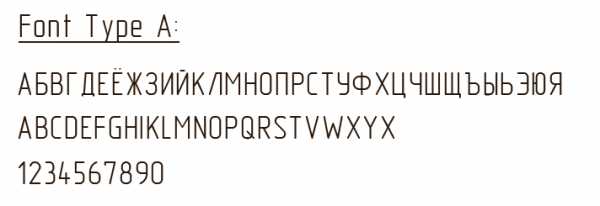
Размер шрифта h — высота прописных (заглавных) букв и цифр измеряемая в миллиметрах. Стандарт устанавливает следующие размеры шрифта: 1,8; 2,5; 3,5; 5; 7; 10; 14; 20; 28; 40. Высота строчных букв определяется по соотношению c = (7/10)h или если шрифт дан An то его высота строчных букв может быть взята по размеру шрифта An-1. Например размер шрифта взятый вами для какой либо надписи 40. Это значит h = 40 и тогда Толщина линий d определяется в зависимости от типа и высоты шрифта, например: — Для шрифта типа A(узкого) d = (1/14)h; — Для шрифта типа Б(широкого) d = (1/10)h. Ширина буквы определяется: — в зависимости от высоты шрифта g = (6/10)h; — толщины линии g = 6d. ![]() Чертежные шрифты Построение прописных букв русского алфавита без наклона ![]() Чертежные шрифты Построение прописных букв русского алфавита без наклона по временной вспомогательной сетке с размером ячейки равным толщине линии. Когда величина букв небольшая, размер ячейки определяется ее шириной и высотой. ![]() Чертежные шрифты Построение строчных букв русского алфавита без наклона Чертежные шрифты Построение строчных букв русского алфавита и цифрового ряда без наклона ![]() Чертежные шрифты тип Б(d = h 1/10) с наклоном около 75° выполненные в масштабе М1:1 №10, №7 и №5: ![]() Чертежные шрифты ![]() Чертежные шрифты Латинский алфавит ![]() Чертежные шрифты Греческий алфавит ![]() Чертежные шрифты Для быстрого и качественного выполнения надписей на чертеже может быть применена специальная линейка, Чертежные шрифты которую несложно изготовить из тонкого твердого картона, вырезав в нем три окна. Левое окно предназначено для написания в нем прописных букв и строчных букв, имеющих верхнее окончание. В среднем окне пишутся обычные строчные буквы. В правом окне пишутся строчные буквы, имеющие нижнее окончание. В случае использования данной линейки необходима минимальная разметка — это линии строк. В качестве примера графической работы с преобладанием темы Чертежные шрифты смотри: Титульный лист + |
Буквы для черчения. Чертежный шрифт. Алфавит. Правила написания прописных букв и цыфр
Шрифт (от нем. Schrift) — это рисунок, начертание букв ка кого-либо алфавита, цифр и знаков.
Шрифты чертежные (ГОСТ 2.304-81) предназначены для выполнения надписей, начертания условных знаков и размерных чисел на чертежах. Для выполнения надписей в черчении используют ГОСТ. ГОСТ устанавливает номера чертежных шрифтов (1,8; 2,5; 3,5; 5; 7; 10; 14; 20; 28; 40) русского, латинского и других алфавитов.
Первый стандарт «Шрифты для надписей» был разработан и утвержден в 1919 г.
Номер шрифта соответствует высоте (h) прописной буквы. Например, шрифт № 5 имеет высоту прописной буквы, равную 5 мм.
Высота буквы измеряется перпендикулярно к основанию строки. Шрифт выполняется с наклоном в 75° (ГОСТом допускается выполнять надписи чертежным шрифтом без наклона).
Для удобства написания букв чертежного шрифта выстраивают вспомогательную сетку (рис. 35), которую выполняют следующим образом. Проводят нижнюю и верхнюю линии строки, расстояние между которыми равно высоте прописной буквы. Откладывают на нижней линии строки ширину букв и расстояние между ними (табл. 3).
Используя углы 45° и 30° угольников, строят наклон букв в строке, равный 75°.
Рассмотрите начертание букв чертежного шрифта (рис. 35— 37). Они различаются наличием горизонтальных, вертикальных, наклонных линий и закруглений, шириной и высотой. На рисунках показана (стрелками) последовательность начертания каждой буквы.
Рис. 35. Начертание прописных букв, состоящих из горизонтальных и вертикальных элементов, и построение вспомогательной сетки
рис. 36. Начертание прописных букв, состоящих из горизонтальных, вертикальных и наклонных элементов
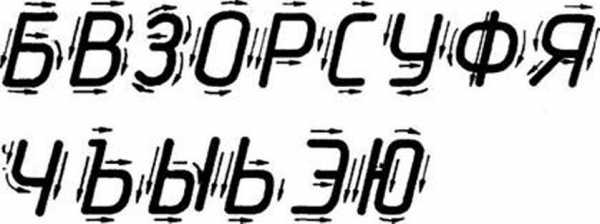
Рис. 37. Начертание прописных букв, состоящих из прямолинейных и криволинейных элементов
Рис. 38. Начертание строчных букв, отличающихся от начертания прописных букв
Как вы, наверное, уже заметили, начертания многих строчных и прописных букв не отличаются между собой, например К — к, О — о и др. Начертание некоторых строчных букв отличается от начертания прописных (рис. 38).
При выполнении надписей следует учитывать, что нижние элементы прописных букв Д, Ц, Щ и верхний элемент буквы Й выполняют за счет расстояния между строк.
3. Размеры букв чертежного шрифта
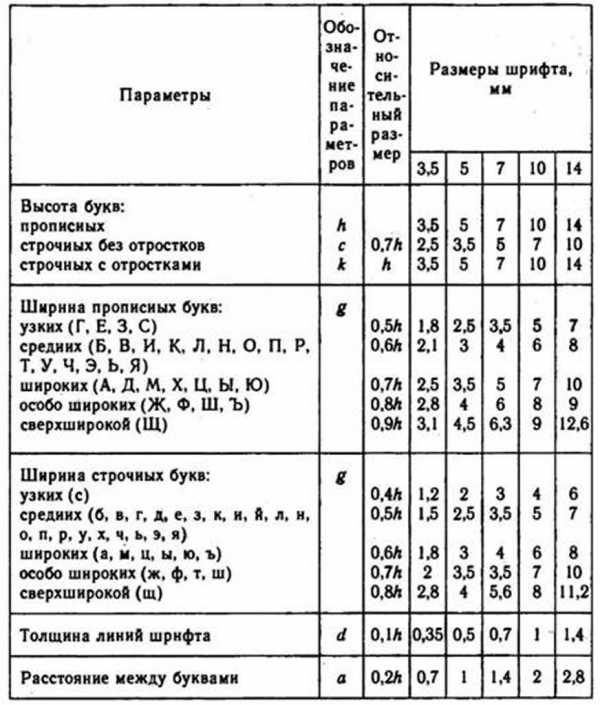
Несмотря на то что расстояние между буквами определено стандартом, оно должно изменяться в зависимости от того, какое начертание имеют рядом стоящие буквы. Например, в слове РАБОТА (рис. 39, а) расстоянием между буквой P и A, T и А необходимо пренебречь (т. е. расстояние должно быть равно нулю), поскольку их начертание зрительно создает достаточный межбуквенный просвет. По этой же причине стандартное расстояние между буквами Б и О, 0 и T следует сократить вполовину. Если такими условиями пренебречь, то буквы в слове будут как бы рассыпаться (рис. 39, б).
Рис. 39. Учет межбуквенного просвета при написании слов: а — правильно; б — неправильно
Рис. 40. Цифры и знаки
Начертание цифр и знаков показано на рисунке 40. (При выполнении чертежей выбирайте высоту шрифта не менее 3,5 мм.)
10 бесплатных и крутых шрифтов / Логомашина corporate blog / Habr
Сегодня рассказываем про шрифты, которые часто используют наши дизайнеры — все они бесплатные, минималистичные и удобные в использовании. Надеемся, наша подборка пригодится вам при выборе шрифтов.Шрифт – часть фирменного стиля, которой нельзя пренебрегать. Форма и начертание букв – основа читабельности и настроения бренда. Текст окружает нас повсюду: название компании, слоган или реклама в журнале. Встречают по одежке. Притягательность текста зависит от того, зацепится ли взгляд за приятные очертания букв или излишние закорючки вызовут отторжение у читателя. Создание шрифтов – наука, но всемирная сеть предлагает неисчерпаемый источник публичных семейств от гуру типографики.
1. Open Sans
Пример использования:
Дизайнер: Стив Мэттэсон – увлеченный дизайнер из штата Колорадо. Более 25 лет Мэттисон разрабатывает шрифты, самыми крупными проектами стали дизайны для Android, Citrix, Microsoft, Nextel и Xbox.
Типы: Light; Light Italic; Regular; Regular Italic; Semi-Bold; Semi-Bold Italic; Bold; Bold Italic; Extra-Bold; Extra-Bold Italic.
Open Sans – приятный для чтения шрифт с простыми формами без засечек. Начертание буквы плавное и широкое. Благодаря своему нейтральному виду шрифт отлично подойдет как для заголовков, так и для основного текста. Шрифт сдержит полный набор символов: латинские, греческие и кириллические. Приятным дополнением станет то, что пакет оптимизирован для печатных, веб и мобильных интерфейсов.
- Курсив и наклон просит минутку внимания: чтобы вежливо уточнить (Italic) или срочно сообщить (Oblique).
- Геометрия отражает жизненные ценности: от уважения к особенностям человека (Гуманистические шрифты) до восхищения футуристическими машинами (Геометрические и Модульные шрифты).
- Статика и динамика передают индивидуальность и богатство внутреннего мира: от нейтральной Гельветики (Статичный рисунок) до старостильных антикв, содержащих пафос своего времени и страны (Динамичный рисунок).